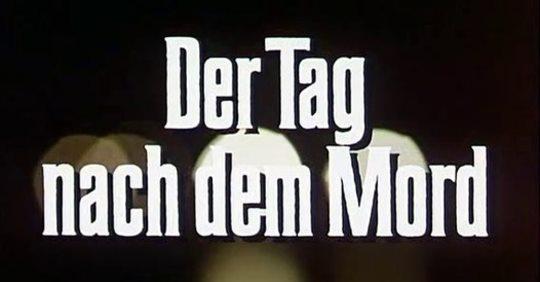
Steilschrift aus DERRICK - verwendet in den frühen 70er Jahren
Aus dem Vorspann einer frühen DERRICK-Folge entstammt dieser Schriftzug. Da er häufig Verwendung fand, gehe ich davon aus, dass er als LETRASET vorlag.
Wer kennt diese Type?